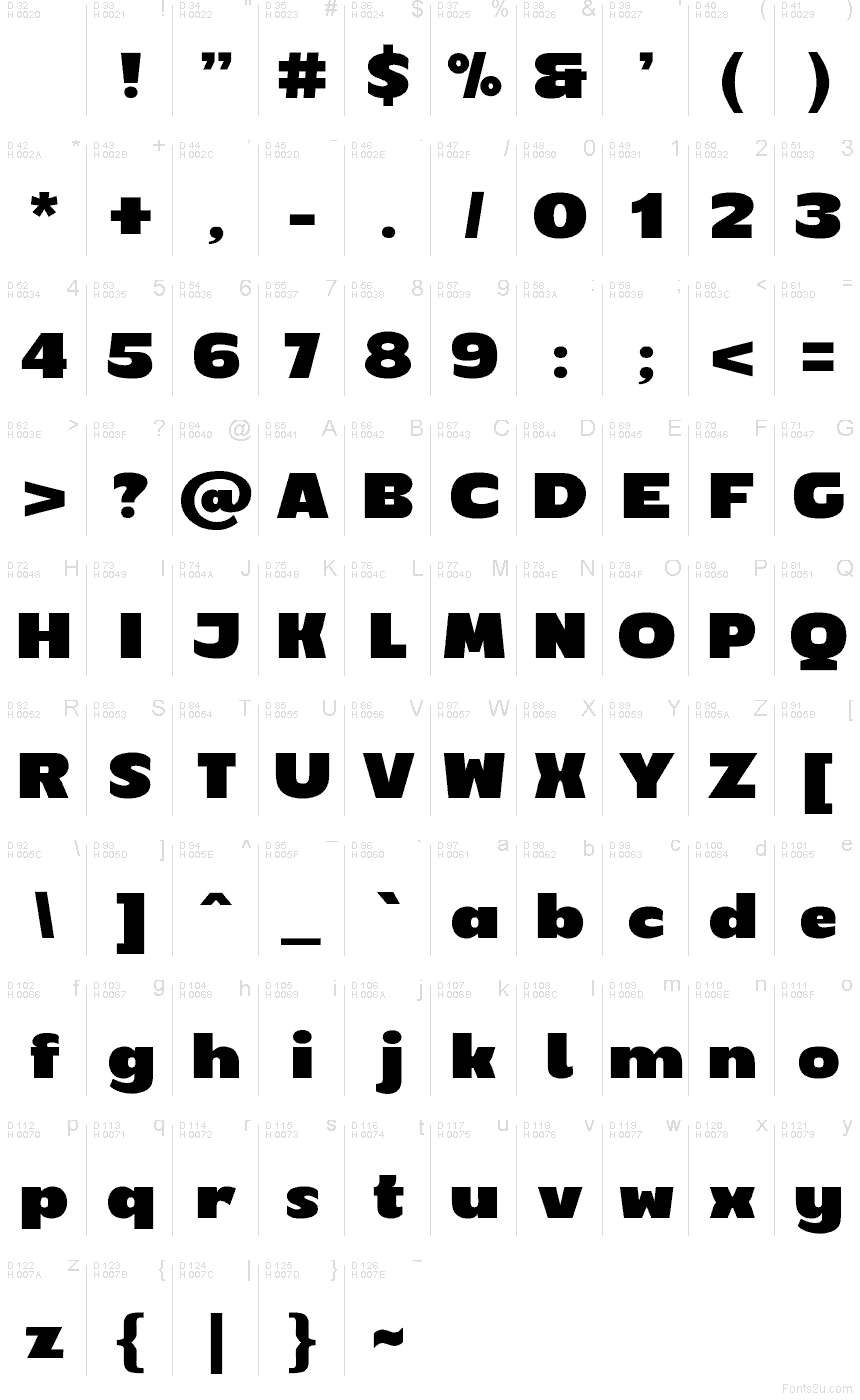
Mertune Bold od Muhamada Fikry Nuralifa z Fikryal Studio je bezpatkový font z rodiny Mertune, který zaujme svými tlustými, téměř polstrovanými tahy působícími velmi sebejistě a sytě. Díky kompaktním vnitřním prostorům znaků a širokým ramenům působí text solidním, blokovým dojmem, takže krátké nápisy vyniknou s patřičnou vahou, aniž by působily příliš složitě.
Mertune Bold využijete pro úderné výsledky v logách, nadpisech, na etiketách produktů, plakátech, náhledech videí na YouTube, úvodních obrazovkách aplikací či sportovní grafice. Při zmenšování písma doporučujeme mírně zvětšit prostrkání (tracking) a jako doplněk pro delší texty zvolit lehký grotesk nebo jednoduché humanistické bezpatkové písmo, aby výrazná povaha Mertune Bold zůstala hlavním prvkem celého designu.